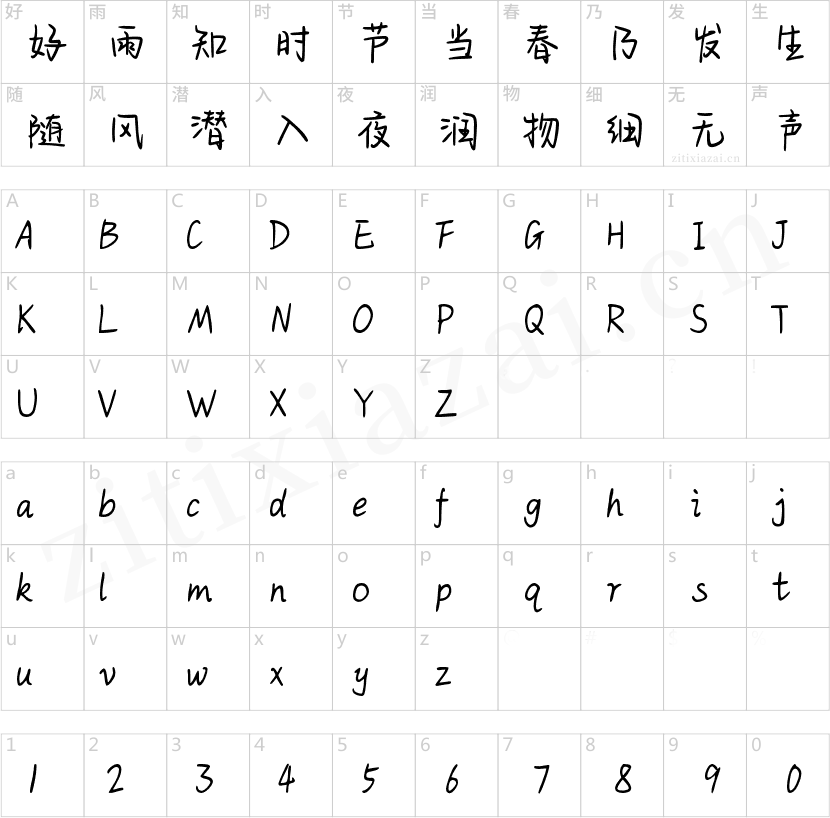
Aa你是浪漫的偏爱
Aa你是浪漫的偏爱,这款字体结构工整、笔画清晰,兼顾美观与易读性,适用于标题、正文、海报、包装、LOGO 等多种场景。字形优雅稳定,风格百搭耐看,适配日常排版与创意设计,让文字呈现更舒适、更具质感。Aa你是浪漫的偏爱一笔一画,皆是细节,以均衡的比例、流畅的线条打造舒适视觉体验,字形端正大气,风格简约现代。无论是商业设计、品牌宣传还是日常排版,都能轻松驾驭,让文字更有格调与力量。Aa你是浪漫的偏爱字体下载。
Aa你是浪漫的偏爱是一款非常具有艺术性的字体,它的设计灵感来源于对古典艺术的研究,同时又融入了现代字体设计的元素。字形优美,笔画粗细变化自然,给人以大气、典雅的感觉。Aa你是浪漫的偏爱是一款既传统又现代的字体,它的设计充满艺术感,美观大方,实用性也非常强。无论是对于设计师还是对于普通读者来说,都是一种非常不错的字体选择。Aa你是浪漫的偏爱适合用于具有艺术感的场合,比如海报、宣传单张、书籍封面等。由于其字形流畅且具有动态感,也适合用于大量的文本排版,如报纸、杂志等。